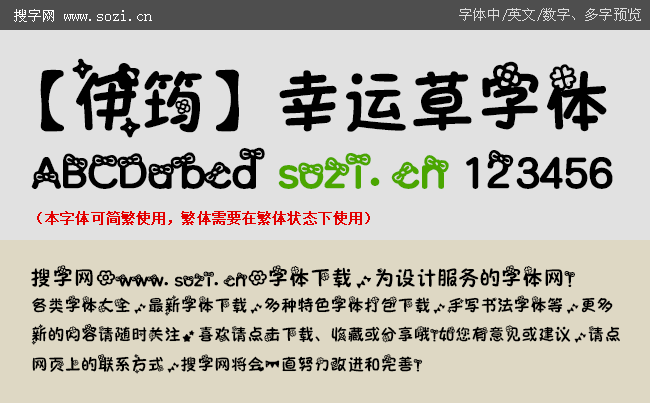
幸運(yùn)草字體
搜字網(wǎng)給大家提供一款卡通手寫風(fēng)格的手機(jī)中文字體下載。名字叫幸運(yùn)草字體,這款手機(jī)字體是仿照兒童手寫風(fēng)格的卡通手寫字體,結(jié)構(gòu)帶有POP字體風(fēng)格,字體間還插入了有趣卡通圖案,特別適合喜歡手機(jī)字體個(gè)性一些的朋友在手機(jī)上安裝使用。